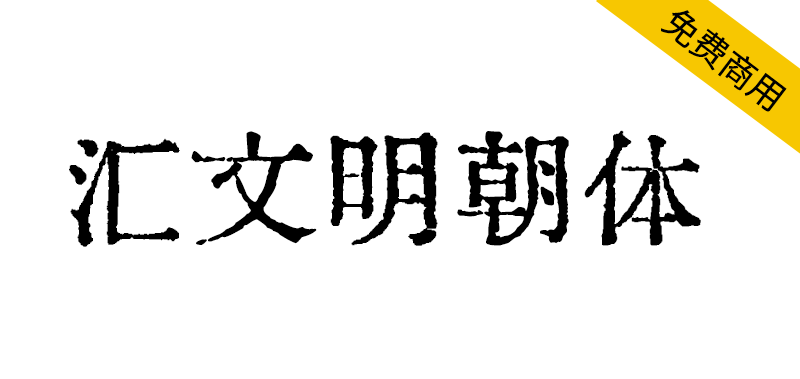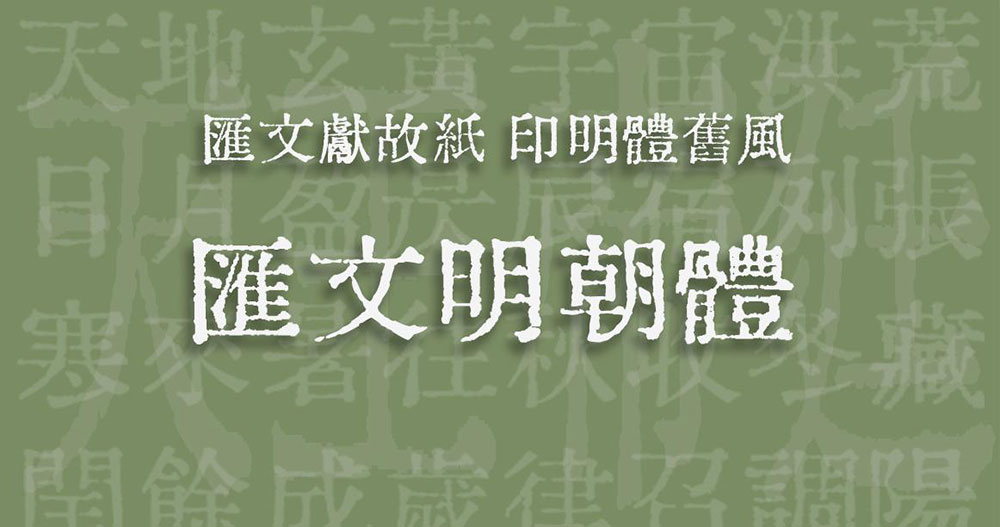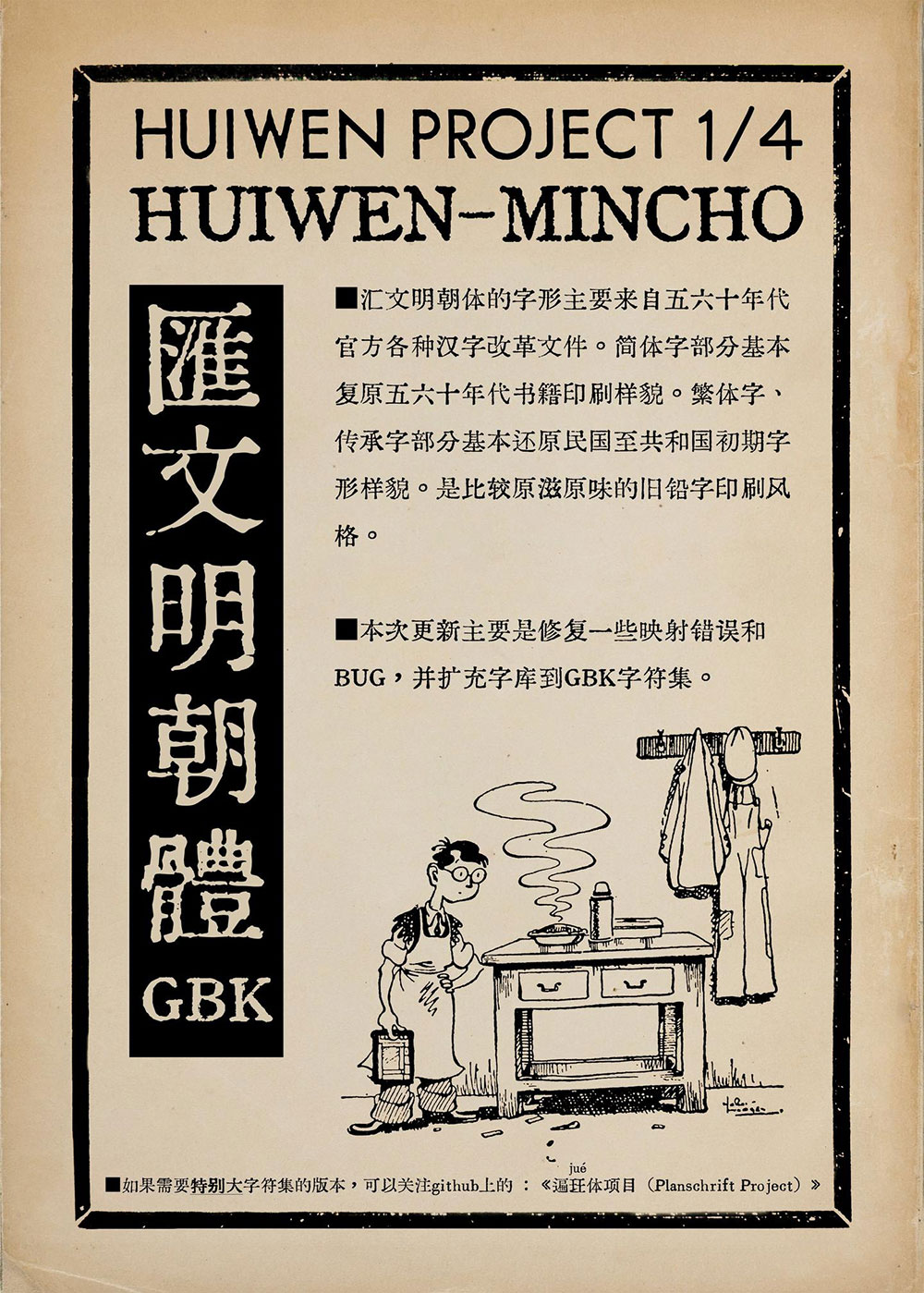
汇文明朝体制作始于2019年1月份。因一切开始于是我扫描《文汇报》上面的《汉字简化方案草案》。后来又收集、扫描了各种历史文献资料,汇总挑选而形成了这样一款字体。故名「汇文明朝体」。本字体的字形来源主体为五六十年代官方各种汉字改革文件。简体字部分基本复原汉字简化后、字形改造前的书籍印刷体样貌。繁体字、传承字部分基本还原民国至共和国初期字形样貌。是比较原滋原味的旧铅字印刷风格。
收录范围规则:全覆盖大陆「GB2312」标准,全覆盖台湾「常用国字标准字体表」,全覆盖日本常用、人名用、表外汉字表中的新字体,基本满足日常使用。